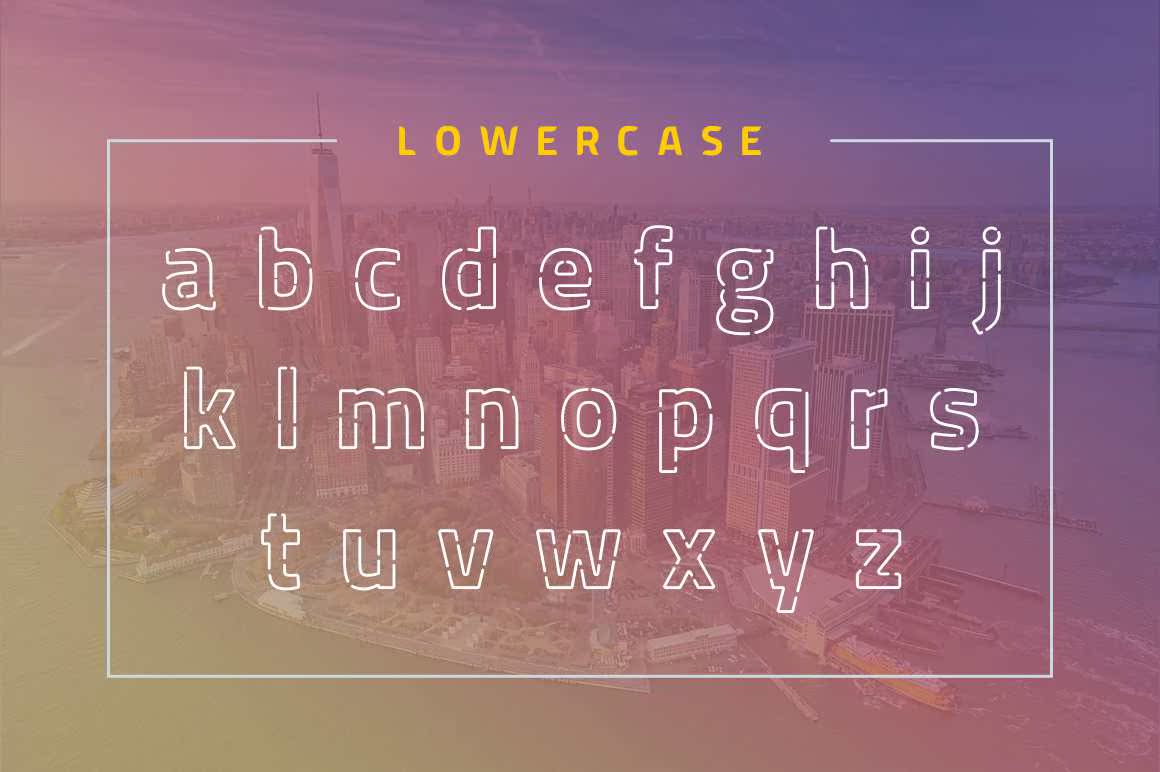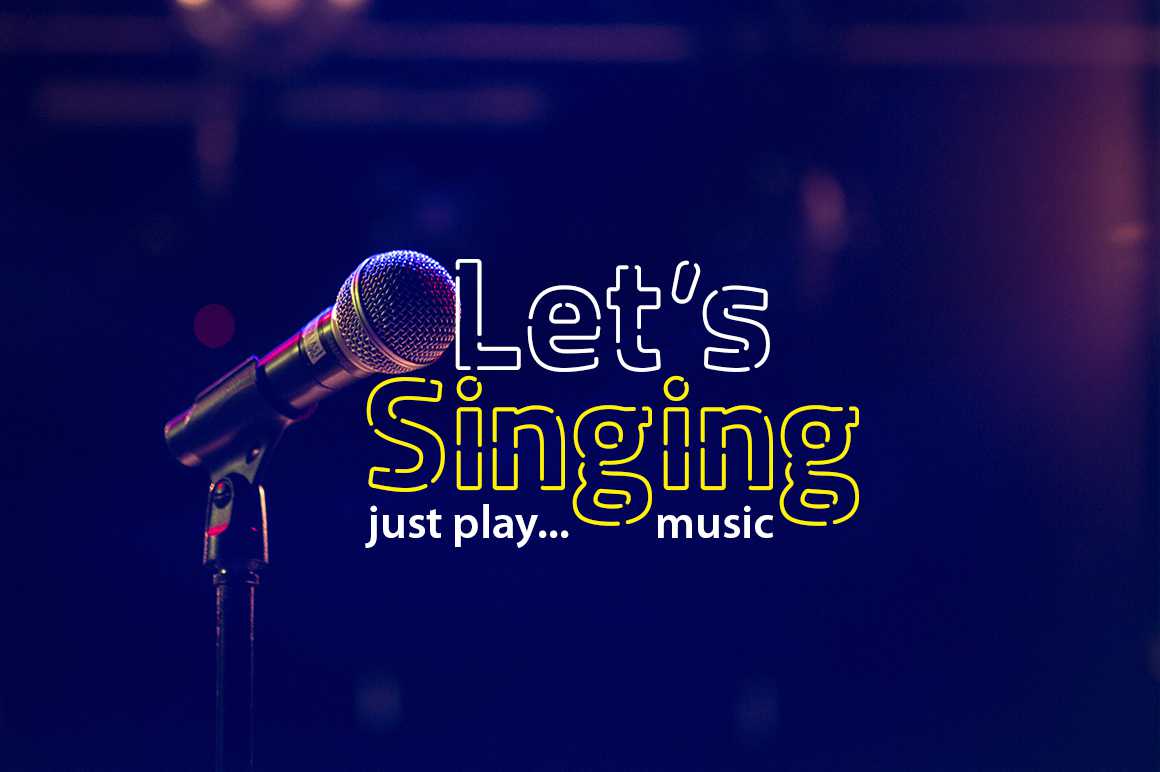
Mexicang Rap完全适用于海报、徽标、音乐封面、服装和许多酷设计项目。Mexicang Rap完全适用于SupperCase和Lowercase.Numericandinternationalfont。Mexicang Rap完全适用于海报、徽标、音乐封面、服装和许多酷设计项目。Mexicang Rap完全适用于SupperCase和Lowercase.Numericandinternationalfont。